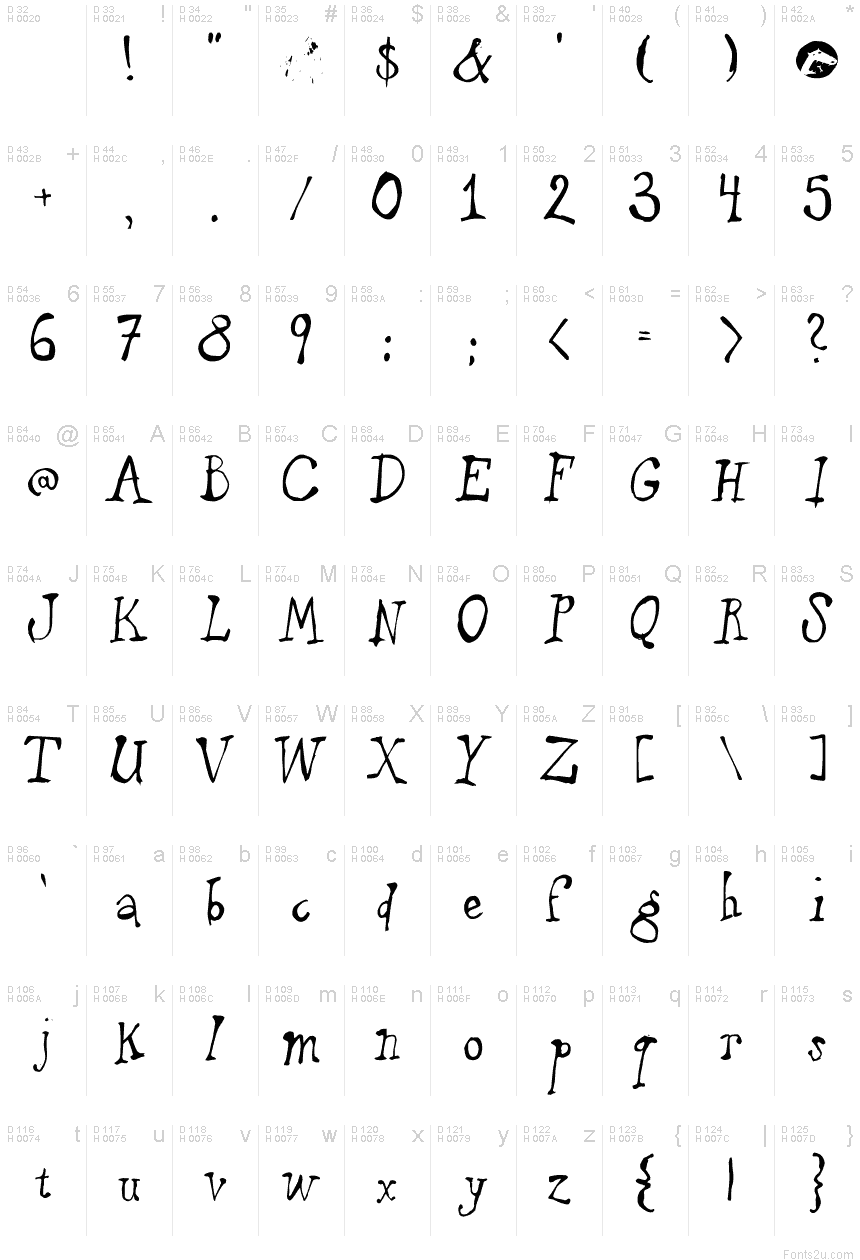
puppetFace
PuppetFace هو خط مجاني مكتوب بخط اليد بأسلوب قصص الأطفال، صممه Claus Kristensen من استوديو Beetles & DryFish fontdesign. يتميز بإيقاع متعرج يشبه خيوط الدمى، مما يضفي طابعاً مسرحياً وغامضاً بعض الشيء. تتمايل الحروف على ضربات طويلة ومستدقة، بينما تحافظ القمم المستديرة والوصلات غير المنتظمة على طابع مرح بعيداً عن الرسمية.
وهذا يجعل هذا الخط المجاني خياراً طبيعياً لأغلفة الكتب، وعناوين الملصقات، وترويسات المجلات المستقلة، وتصاميم حفلات الهالوين، والتغليف المبتكر حيث يمكن للحروف أن تصبح جزءاً من المشهد. كما أنه يعمل بشكل جيد مع العناوين القصيرة أو الشعارات، لأن تلك الضربات الرأسية المتدلية تمنح حتى مجموعة صغيرة من الحروف صورة ظلية حيوية ومتحركة.